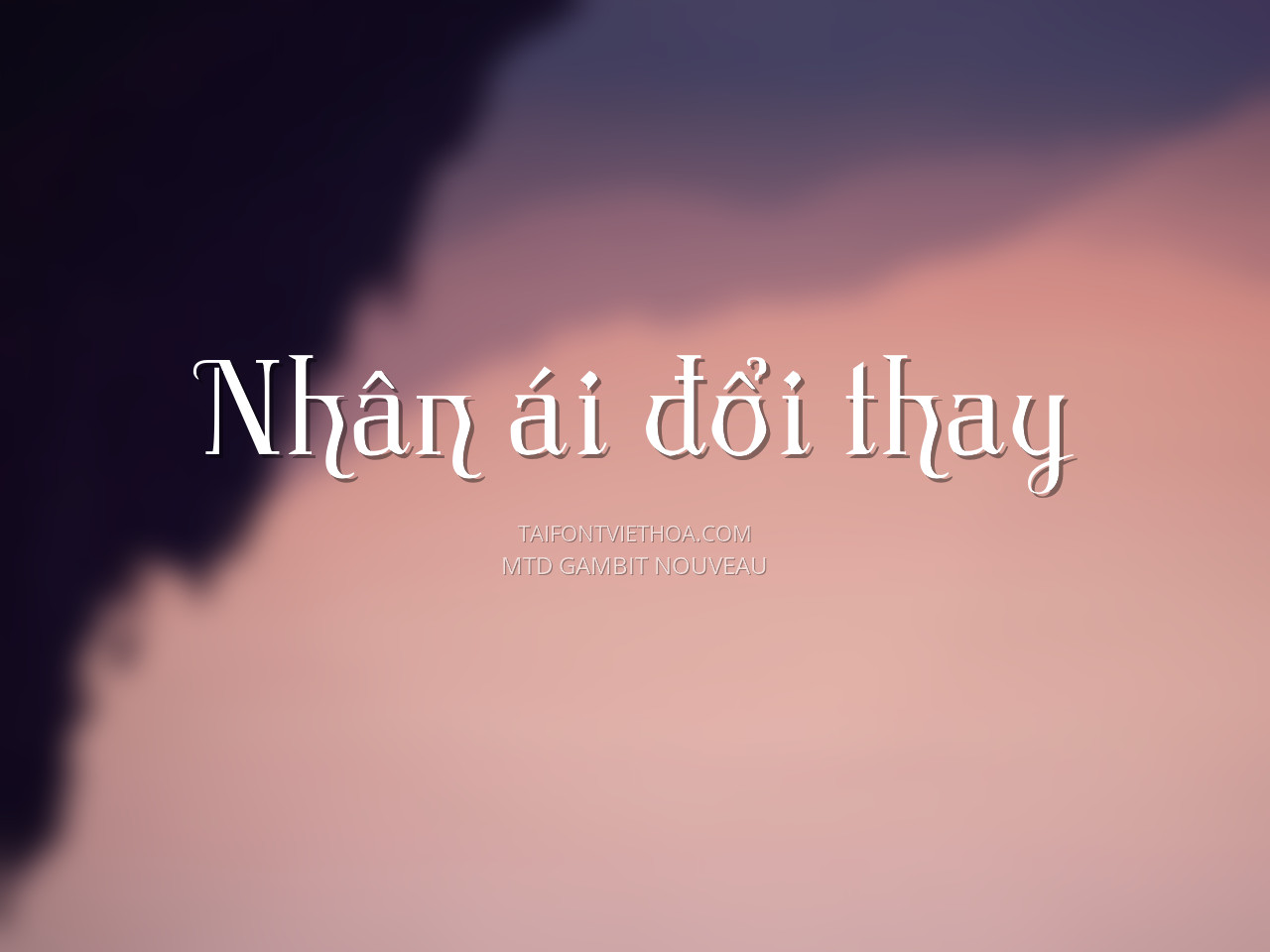
Font việt hóa MTD Gambit Nouveau
Giới thiệu về font Gambit Nouveau
Gambit Nouveau là một font display độc đáo lấy cảm hứng từ phong trào nghệ thuật Art Nouveau, được thiết kế bởi Motokiwo Type (MTD). Font nổi bật với các đường nét cách điệu, uốn lượn mềm mại kết hợp hình khối trang trí mang màu sắc hoài cổ nhưng vẫn giữ được sự hiện đại cần thiết. Đây là kiểu chữ phù hợp cho các thiết kế cần tạo ấn tượng mạnh về mặt thị giác, thể hiện sự sáng tạo và khác biệt. Phiên bản Việt hóa được chính MTD thực hiện, hỗ trợ đầy đủ tiếng Việt cùng hơn 70 ngôn ngữ quốc tế.
Đặc điểm thiết kế và ứng dụng của font Gambit Nouveau
Font sở hữu những đường cong nghệ thuật đầy biểu cảm, các nét dày mỏng xen kẽ tạo nên sự chuyển động tinh tế trong từng ký tự. Đặc trưng của phong cách Art Nouveau thể hiện rõ qua cách các chữ cái được trang trí với chi tiết uốn lượn, lồng ghép hình khối mạch lạc, dễ nhận diện. Font này không phù hợp cho văn bản dài nhưng cực kỳ hiệu quả khi dùng làm tiêu đề, logo hoặc điểm nhấn trong thiết kế đồ họa.
Ứng dụng lý tưởng: thiết kế poster nghệ thuật, logo, bìa sách, bao bì mỹ phẩm hoặc thời trang, tiêu đề website, namecard sáng tạo và các ấn phẩm quảng bá thương hiệu. Ngành nghề phù hợp: thời trang cao cấp, mỹ phẩm, studio nghệ thuật, nội thất phong cách, thiết kế sáng tạo, thủ công và các thương hiệu cần tạo dấu ấn thị giác mạnh mẽ.